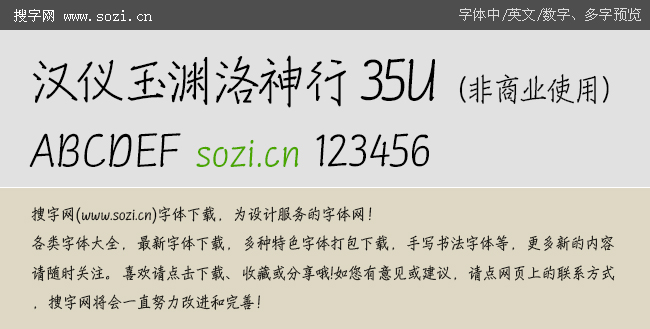
汉仪玉渊洛神行 35U
搜字网给大家提供一款汉仪玉渊洛神行 35U中文字体下载,汉仪洛神行取意赵孟頫行书《洛神赋》卷,行中兼楷,在字形结构上寻求“竦轻躯以鹤立,若将飞而未翔”的意境,结合现代等线的笔画设计,保留行楷的流畅潇洒而减弱古旧气息。汉仪洛神行的字形偏长,中宫略小而笔画舒展,挺拔如鹤立。重心平稳,字形略带书写的自然倾斜,呈现“若将飞而未翔”之势。适用于画册设计、海报设计、包装设计等场合使用。(本字体为个人非商用版,如需要商用请联系汉仪公司购买版权)